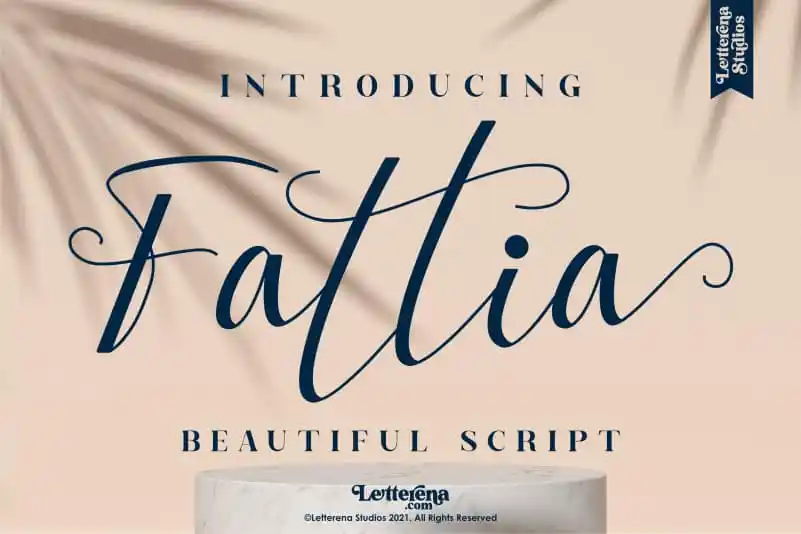
Fattia Script Font – Download Grátis
A Fattia Script Font é uma elegante fonte de estilo script criada por Letterenastudios. Seu charme romântico a torna perfeita para diversos projetos, desde criação de logotipos e embalagens até design de roupas e estampas personalizadas. Suavemente fluida, ela se destaca em trabalhos como cartões de convite, capas de livros e caixas de mão, oferecendo um toque delicado a qualquer projeto de arte digital. Ideal para aqueles que buscam uma fonte única e sofisticada para dar um toque personalizado em suas criações, seja para projetos do dia a dia ou espetaculares eventos especiais.